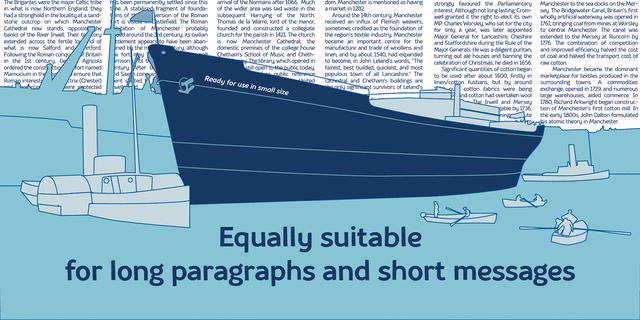
Souses – оригинальный шрифт, сделанный вручную. Классический набор начертаний: Тонкий, Светлый, Нормальный, Жирный, Сверхжирный + наклонные начертания. Этот шрифт идеален для использования в таких тематиках как: экология, пищевая промышленность, хендмейд, игрушки. Рукотворный неформальный стиль начертаний – это важное преимущество, которое помогает вызывать лояльность к вашему продукту и компании. Souses оптимизирован для сайтов, мобильных приложений и печатной продукции. Шрифт Разработан Иваном Гладких в студии TypeType в 2014 году.
Ассоциации c семейством TT SousesКачества и характер:
минималистичный, деликатный, легкий, прохладный, свежий, тонкий, лаконичный, городской, интимный, хрупкий, проволочный, динамичный, рукотворный, живой, неряшливый, игривый, непоседливый, подвижный, худой, простой, доступный, элементарный, комфортный, удобный, дружелюбный, приветливый, остроумный, доверительный, неформальный, молодежный, сильный, убедительный, важный, мотивирующий, спелый, вкусный, заметный, броский, наивный, пьяный, карикатурный, мультяшный, вернакулярный, твердый, значительный, тяжелый, грубый, яркий, активный